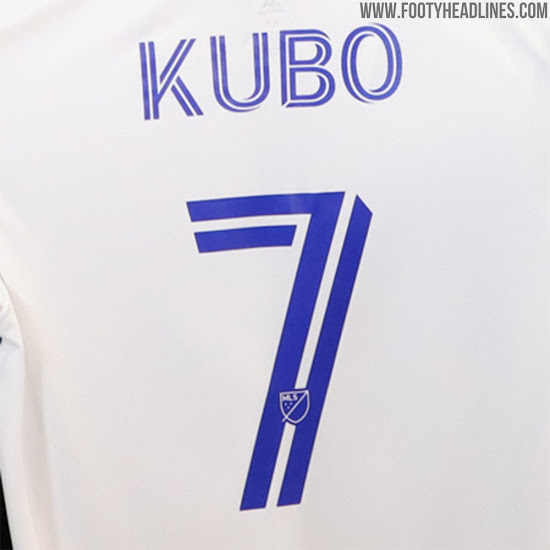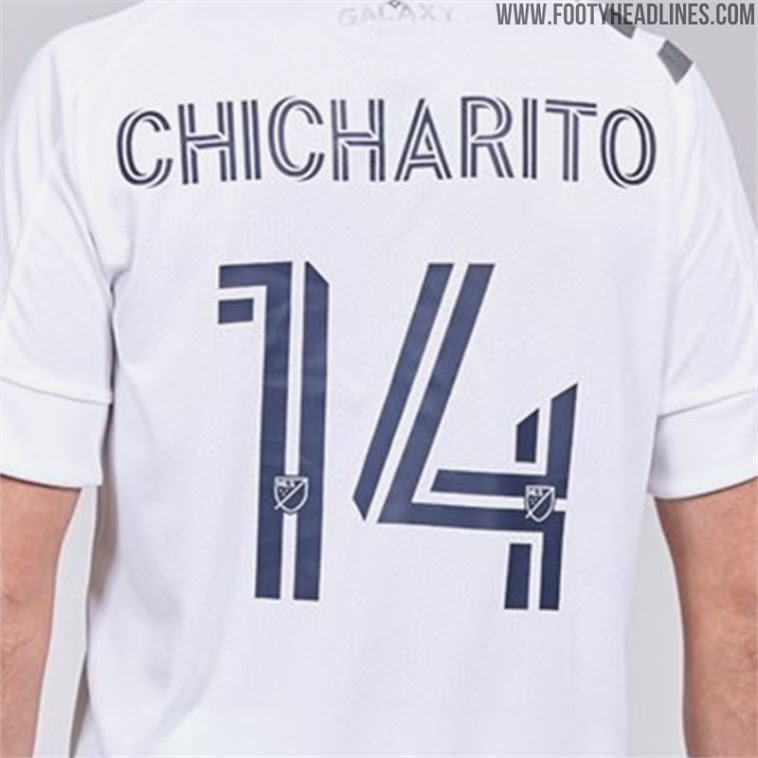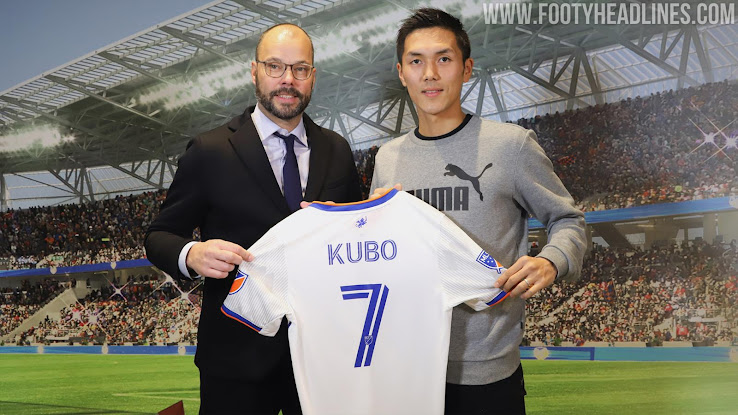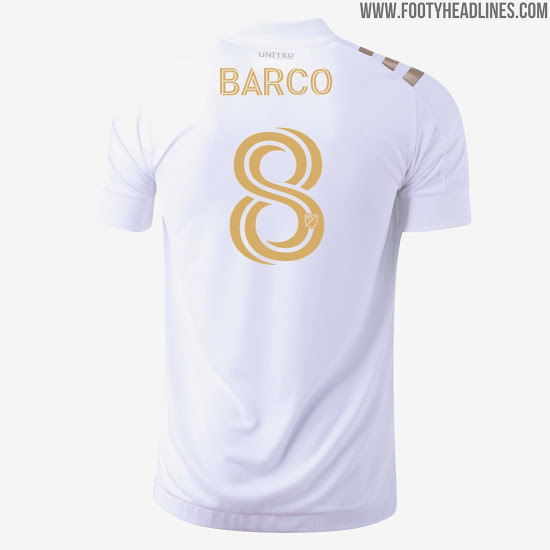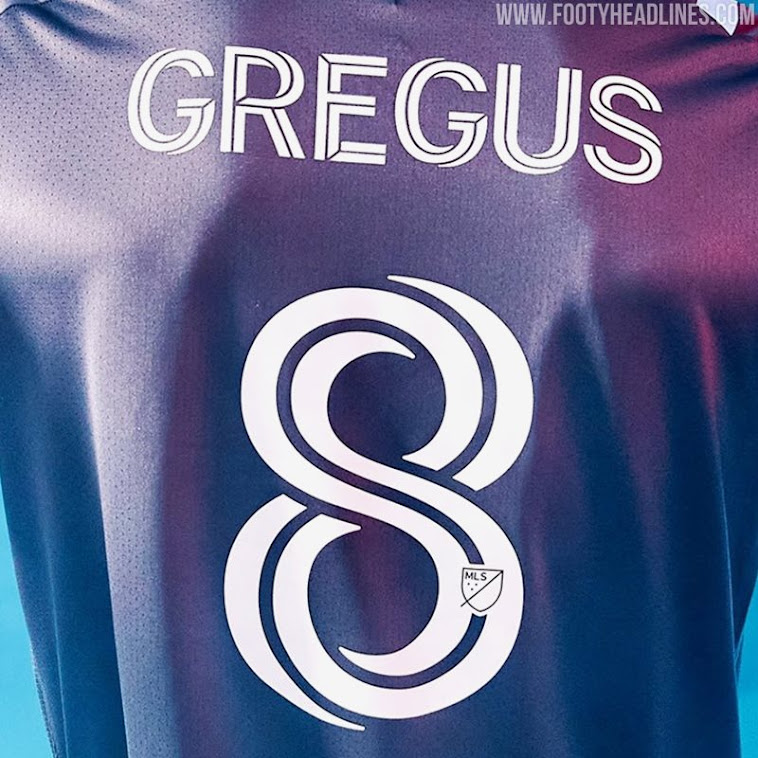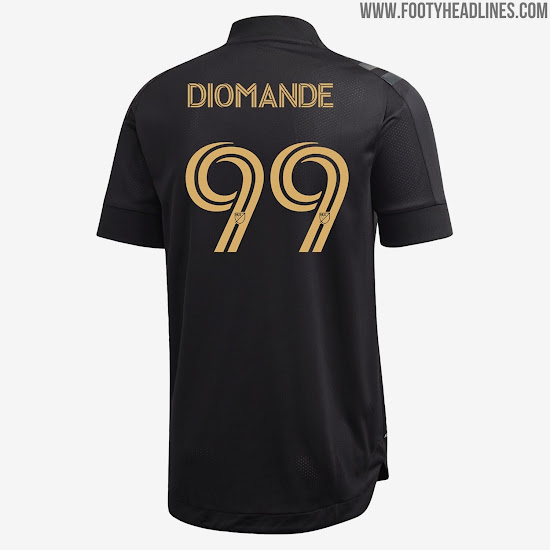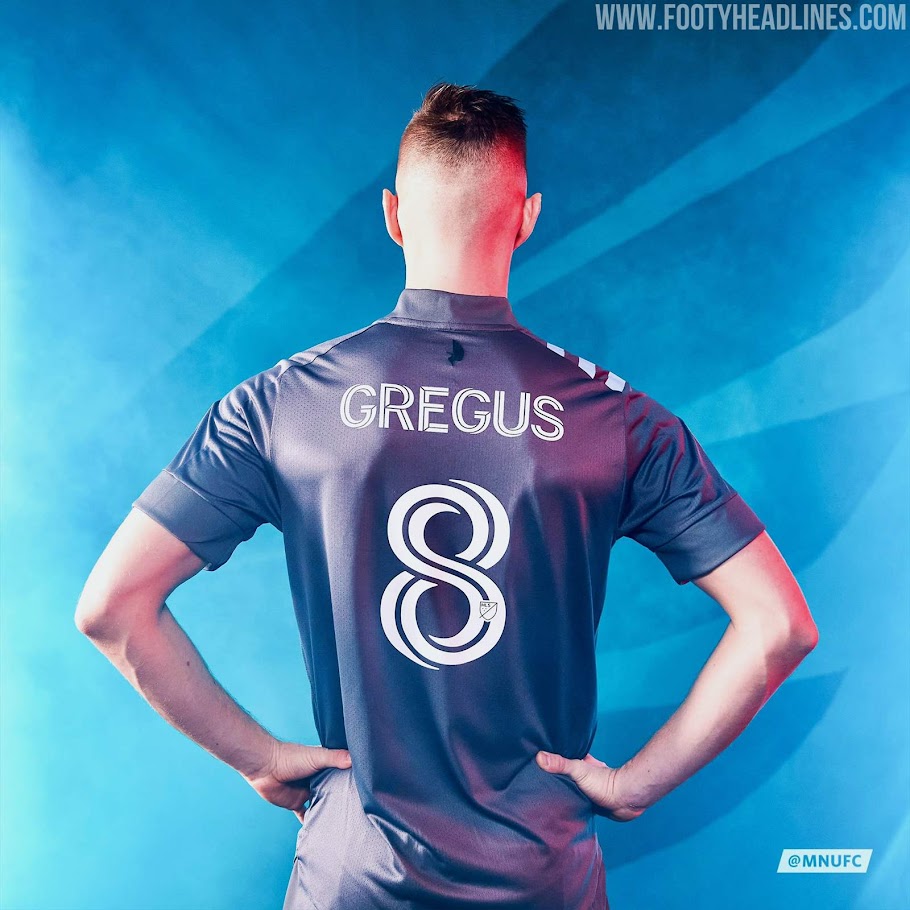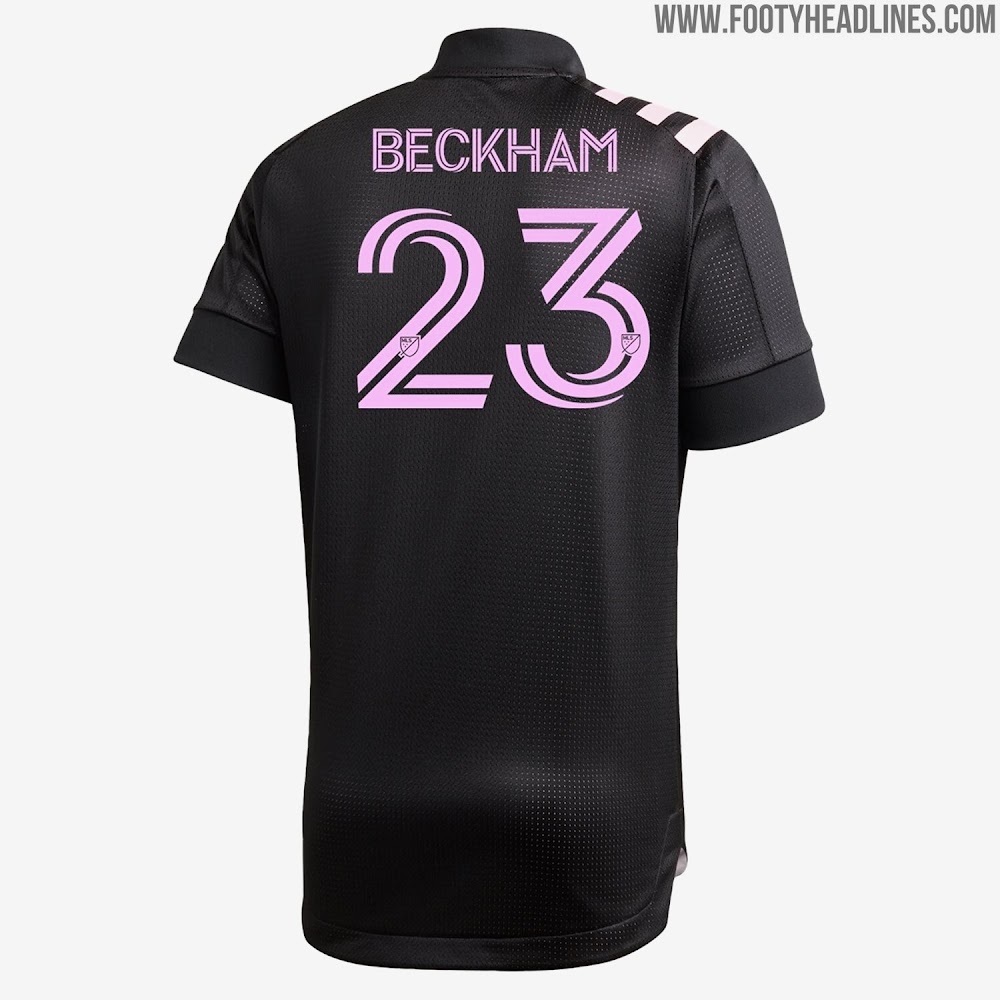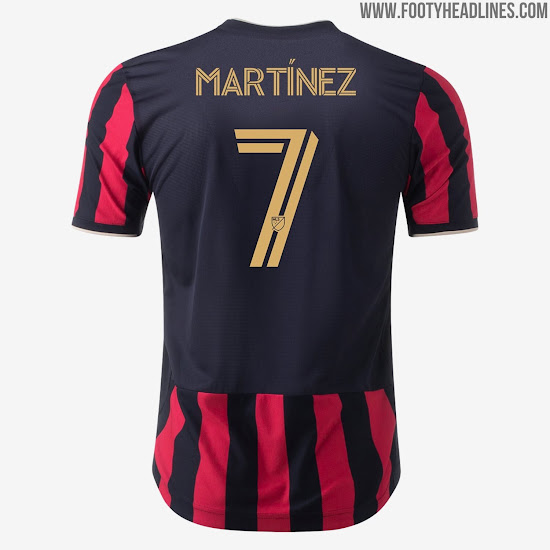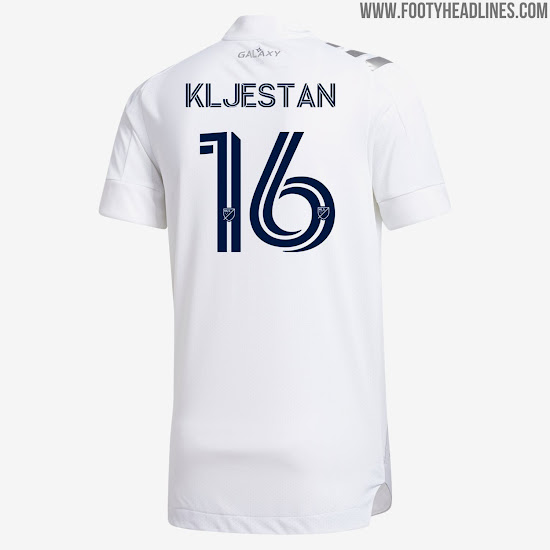
Brandneue MLS 2020 Trikot-Schriftart vorgestellt - drei "verschiedene Versionen"
F37 Foundry, das Studio, das die MLS 2020 Trikot-Schriftart entworfen hat, hat den Designprozess und alle Designdetails der neuen MLS 2020 Schriftart offiziell enthüllt. Es gibt drei unterschiedliche Versionen der Schriftart (Drei Gewichtge, die aufeinander liegen, woraus eine "tri-line" entsteht).
David Bruce - Vizepräsident der Marke MLS- sagte: "Wir haben F37 wegen ihrer Erfolgsgeschichte in der Welt der Schriftarten ausgewählt, was wir lange bewundert haben. Ihre Fähigkeit, unsere Bedürfnisse zu interpretieren und in Form eines verlockenden Designs umzusetzen, war von Anfang an klar. Die Arbeit passt zum Ton unserer Marke, kulturell fließend, fortschrittlich und modern. Sie haben unsere Denkweise in diesem Prozess vorangetrieben, unsere Meinung vom Rahmen des Möglichen erweitert und etwas Größeres als ein paar Namen und Nummern für Trikots erschaffen. Rick war ein großartiger Zuhörer, ein fehlerfreier Kollaborateur und schnell."
Alle Major League Soccer 2020 Trikots wurden am 5. Februar 2020 veröffenthlicht.
MLS 2020 Trikot-Schriftart
Die neue MLS 2020 Trikot-Schriftart "ist eine dynamische, energische und mutige grafische Schriftart, die einen dreilinigen Schichten-Effekt einführt". Die Schriftart ist vom Design klassischer Schriftarten inspiriert und gleichzeitig sehr modern.
Wie die MLS auf ihrer Website verrät, "wurde die offizielle MLS Trikot-Schriftart für Namen und Nummern im Jahr 2020 in Zusammenarbeit mit der MLS von Rick Banks, Lead Designer und Typograph von Face37, einem preisgekrönten Grafikdesign-Studio mit Sitz in Manchester, England, entworfen".
Die Schriftart setzt auf drei Gewichte und sobald diese aufeinandergelegt werden, erschafft es eine "tri-line", etwas vollkommen neues im Bereich der Schrift auf Fußballtrikots. Das sorgt für einen energiegeladenen optischen Effekt, der die Bewegung und Energie im Spiel verkörpert, wie ein Beckham-Freistoß oder ein Ilsinho-Übersteiger. Die tri-line steht symbolisch auch für die drei Sterne, die im Logo zu finden sind. Wo es möglich ist, folgt der Winkel der Nummer den Punkten der drei Sterne im MLS-Logo.
Wie ein vielseitiger Spieler, der auf jeder Position glänzen kann, ist die MLS-Schriftart vielseitig einsatzbar, um zu verschiedenen Anlässen verwendet zu werden - MLS Streets steht auf Trikot und Hose, während die anderen Gewichte verwendet werden können, nach Gutdünken der Liga, auf Bannern rund um Stadien, online und für Social Media.
F37 Foundry, die im Hinterkopf hatten, dass Fußballer vieler Nationalitäten in der Liga spielen, arbeitete an viel Unterstützung von Sprachen, darunter viele Akzente, Doppelbuchstaben und Kleinbuchstaben, um jegliche Eventualität abzudecken, die wir uns vorstellen könnten. Wir haben auch eine insbesonders zusammengefaste Schriftart für längere Namen gestaltet (der lettische Spieler Andriuškevičius kommt sofort in den Kopf).
Die MLS 2020 Trikot-Schriftart wird für alle MLS-Trikots ab 2020 verwendet, einschließlich der Trikots, die bereits in den letzten Jahren veröffentlicht wurden und übernommen werden.
Es ist noch nicht bekannt, ob die MLS 2020 Schriftart nur im nächsten Jahr oder über 2020 hinaus verwendet wird. Wir gehen davon aus, dass die Schriftart noch einige Jahre verwendet wird.